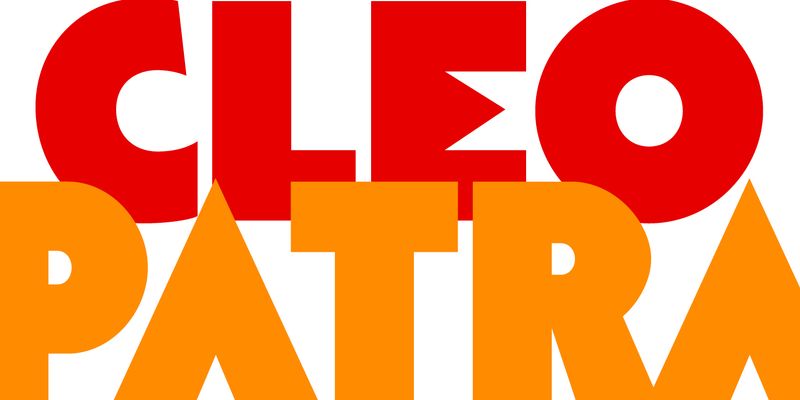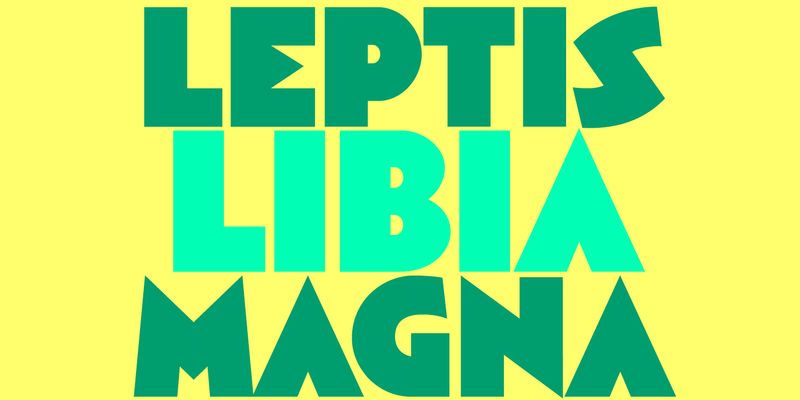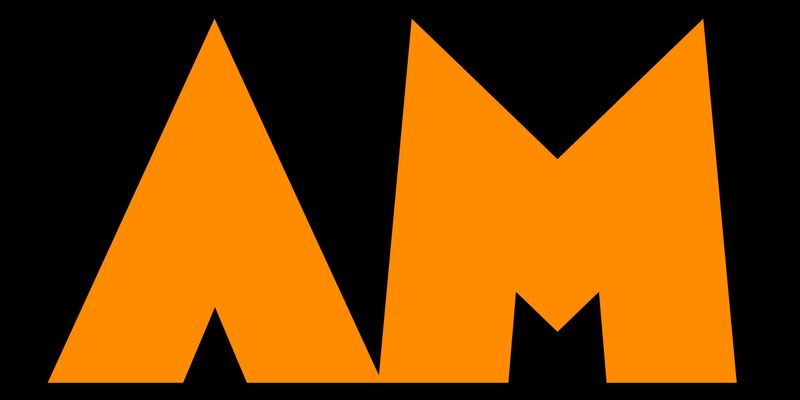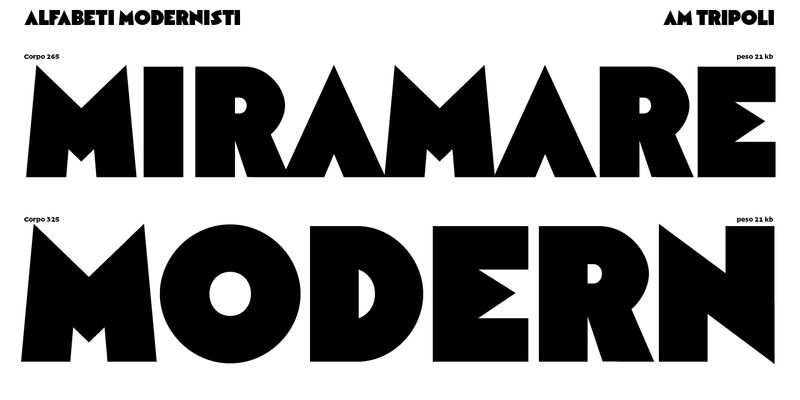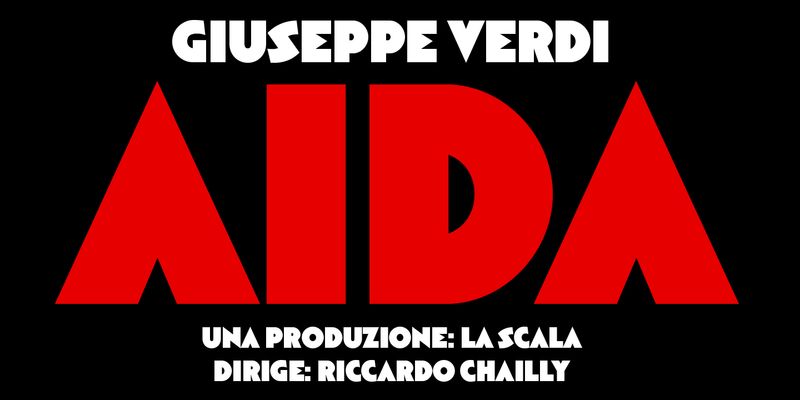
Tripoli ist eine dunkle, serifenlose Versalschrift mit stark expressionistischer Anmutung. Die geometrischen Formen der Buchstaben zeichnen sich durch leicht abgeflachte Bögen, kleine Punzen (Buchstabeninnenräume) und scharfe Kanten sowie ungewöhnlich scharfe Dreiecksformen in den Mittelstrichen von „E“ und „F“ aus. Einige Bögen wurden durch geschwungene Linien ersetzt, die abrupt in scharfe Winkel übergehen, z. B. beim Buchstaben „S“ und der Ziffer „3“.
Tripoli wurde von Xilografia Italiana mit Sitz in Badia Polesine, zwischen Verona und Rovigo, als Holzschrift auf den Markt gebracht. Der historische Kontext lässt vermuten, dass dies kurz nach der Gründung des Unternehmens im Jahr 1934 geschah. Tripolis ist die Hauptstadt Libyens. Anfang der 1930er-Jahre förderte Mussolini die massenhafte Ansiedlung italienischer Kolonisten in Libyen, nachdem italienische Truppen in einem brutalen Kolonialkrieg zahlreiche Kriegsverbrechen gegen die libysche Bevölkerung begangen hatten.
Insgesamt wirken die Buchstaben der Schrift Tripoli wie von Hand geschnitten. Ihre Anmutung vermittelt den Eindruck des „Ungeplanten und Zufälligen“. Tripoli ähnelt stilistisch der Schrift „Neuland“, die 1923 von Rudolf Koch entwickelt und von dem britischen Typografen, Schriftgestalter und Autor Walter Tracy beschrieben wurde. Neuland wiederum wurde vermutlich von Wiener Künstlern wie Oskar Kokoschka mit seinen kühnen, expressionistischen White-Paper-Schriften beeinflusst. Dieser Stil war Anfang des 20. Jahrhunderts in ganz Mitteleuropa als Plakatschrift beliebt und bildet die Grundlage für das Design von Tripoli.
Die digitale Neuauflage, AM Tripoli, enthält die Buchstaben der zugrunde liegenden Holzschrift in sorgfältig korrigierter und fein abgestimmter Form. Der Designer Alessandro Bombieri erläutert: „Zusätzlich zu den notwendigen visuellen Verbesserungen wurden zahlreiche Mängel in den Konturen der Holzschrift korrigiert. Sie sind zwar in der digitalen Schrift sichtbar, ohne jedoch zu stören oder abzulenken. Die Buchstabenabstände wurden optimiert und gestrafft, um zeitgemäßen Satzstandards zu entsprechen.“